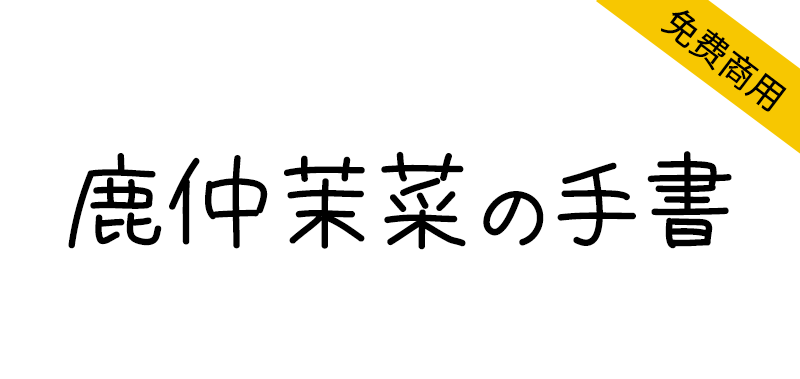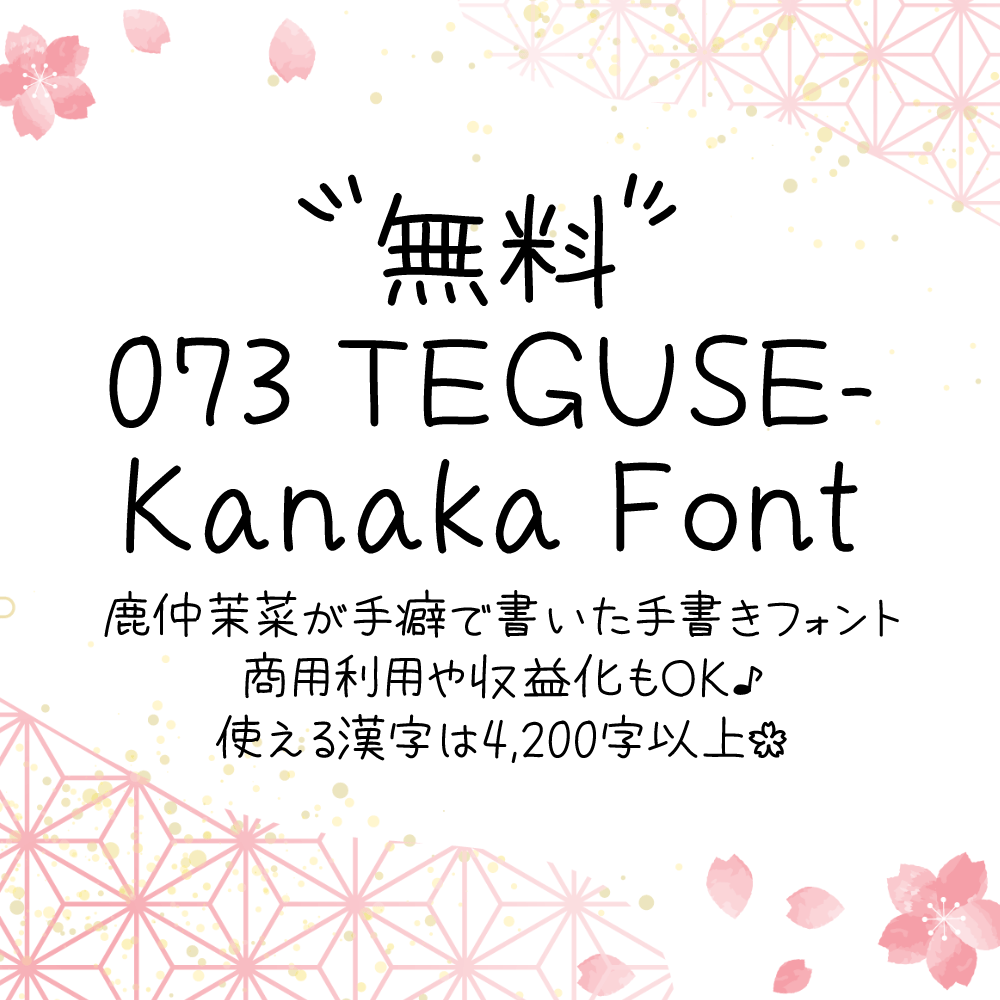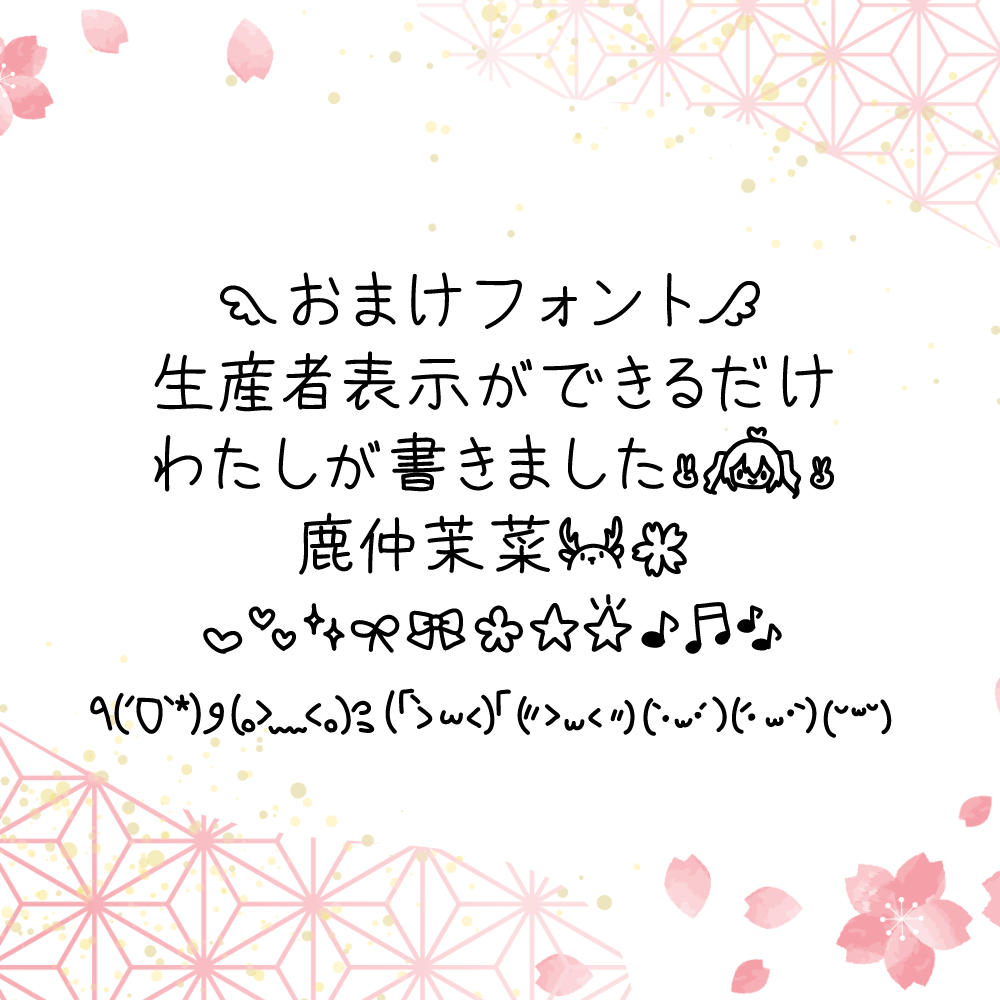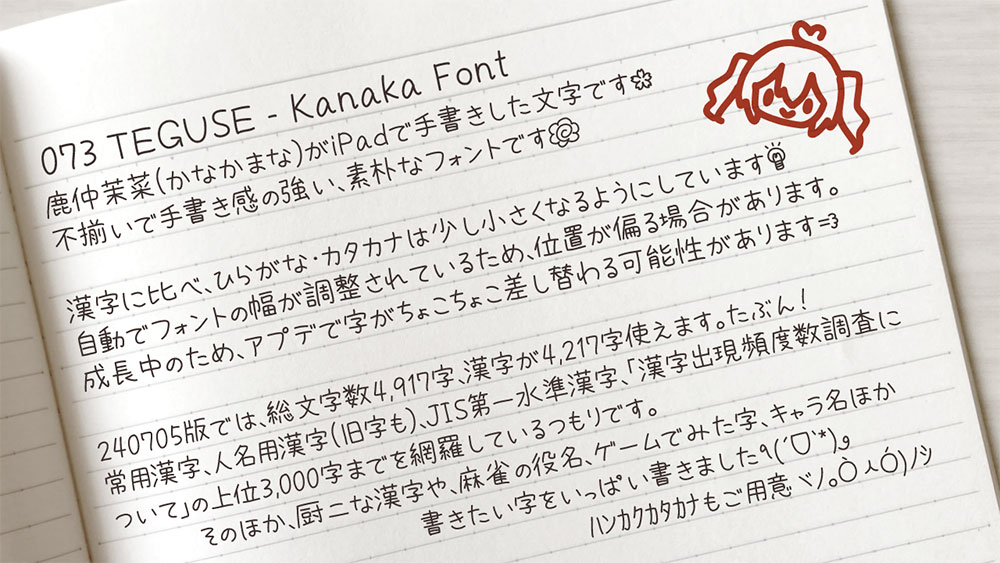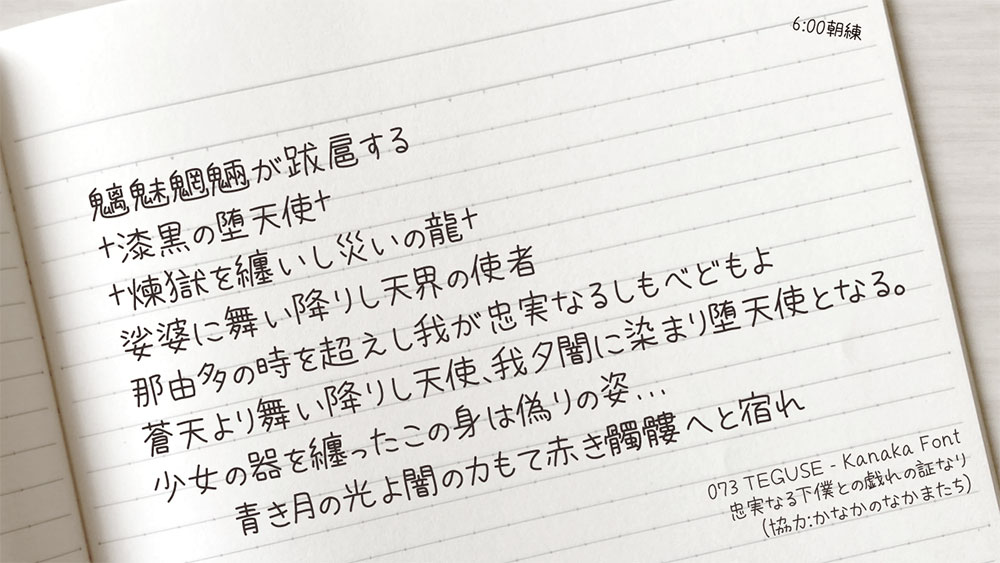
【鹿仲茉菜の手書】不整齐,手写感强,朴素的日语字体
这是鹿仲茉菜的手写字体。
是不整齐,手写感强,朴素的字体。
与汉字相比,平假名、片假名要小一些。
自动调整字体宽度可能会导致位置偏移。
这个字体正在成长中。因为自己试着使用觉得平衡不好,或者觉得不擅长的字随时都在修改,所以在应用程序中字有可能会稍微改变。
鹿仲茉菜(かなかまな)の手書きフォントです。
不揃いで手書き感の強い、素朴なフォントです。
漢字に比べ、ひらがな・カタカナは少し小さくなるようにしています。
自動でフォントの幅が調整されているため、位置が偏る場合があります。
このフォントは成長中です。自分で使ってみてバランスが悪いなと感じたり下手っぴすぎるなと思う字は随時修正しているので、アプデで字がちょこちょこ差し変わる可能性があります。